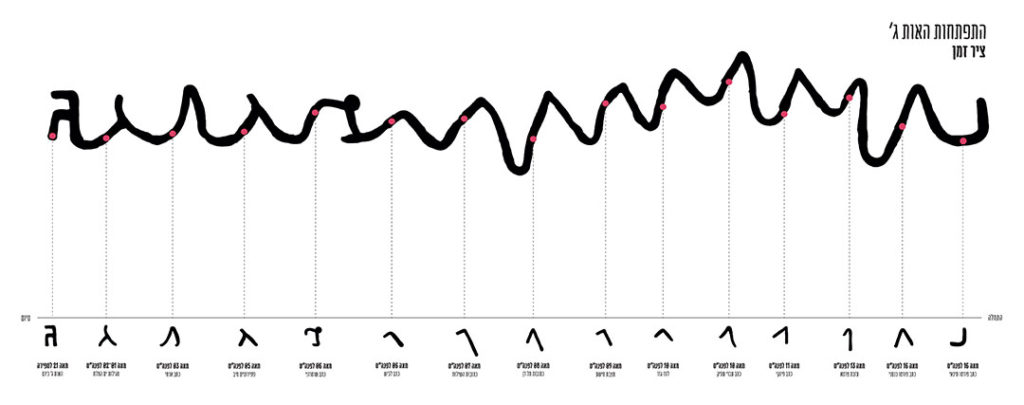
תולדות האות העברית או: ״כיצד נוצרה האות העברית?״
מאת: נעם רמתי יצאתי לחקור את התהליך הצורני שעברה האות העברית לאורך ההיסטוריה, עד שהגיעה לצורתה הנוכחית המוכרת לנו היום. התעמקתי במספר אותיות אקראיות – א’, ג’, ו’, צ’, ק, ו־ש’. לאחר מחקר צורני מעמיק, הצגתי את התהליך שכל אות עברה בפורמט משתנה, תוך ניסיון ללמד את הצופה את ההתפתחויות השונות בדרכים אחרות. האותיות עצמן … המשך לקרוא תולדות האות העברית או: ״כיצד נוצרה האות העברית?״